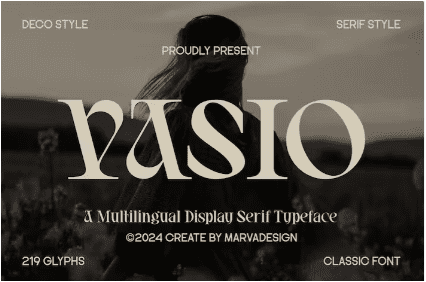
Vasio - Classic Display Serif Font
Представляем наш новый продукт Vasio - классический шрифт с засечками для дисплея Vasio - Этот шрифт имеет элегантный декоративный стиль с засечками, все расстояния в пространстве выполнены одинаково, этот шрифт подходит для использования в различных продуктах, таких как: уход за кожей, косметика, логотипы, брендинг,
журналы и плакаты. Выдающийся в самых разных контекстах.